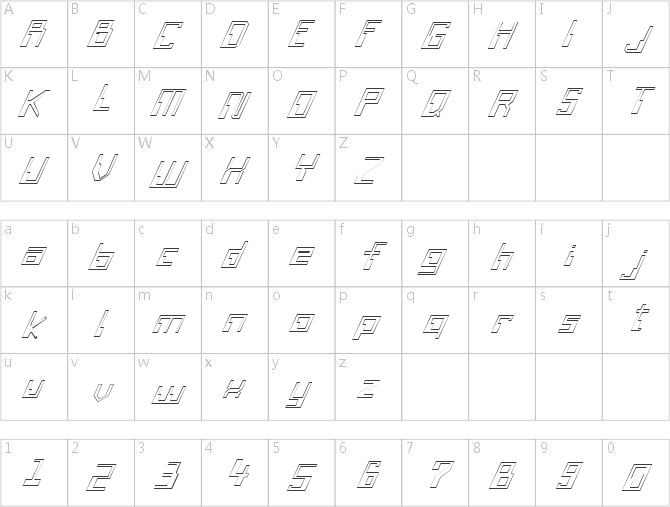
FZ DIGITAL 6 HOLLOW ITALIC 詳情頁
FZ DIGITAL 6 HOLLOW ITALIC字體字庫是一款讓人賞心悅目、百看不厭的英文字體,適合各類廣告和產(chǎn)品包裝設(shè)計應(yīng)用,字體大小0.04MB,格式為ttf字體,上傳用戶是Elieen,作者/版權(quán)方為未知